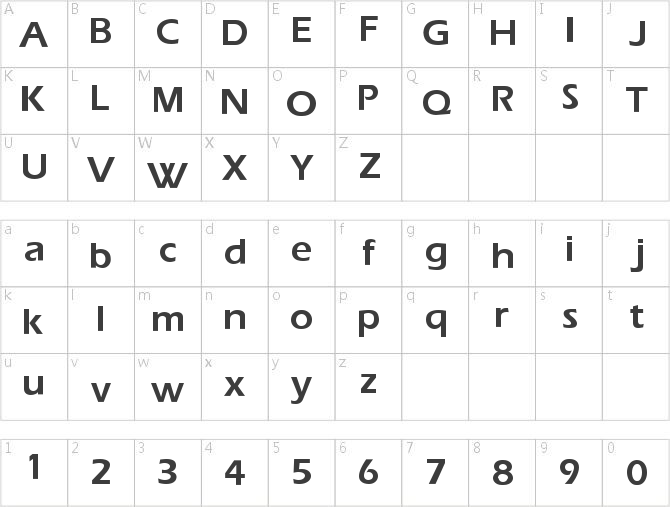
Eras-Black-SemiBold(1) 详情页
Eras-Black-SemiBold(1)
Eras-Black-SemiBold(1)介绍
Eras-Black-SemiBold(1)字体字库是一款让人赏心悦目、百看不厌的英文字体,适合各类广告和产品包装设计应用,字体大小0.03MB,格式为ttf字体,上传用户是东方时尚,作者/版权方为未知
Eras-Black-SemiBold(1)效果图